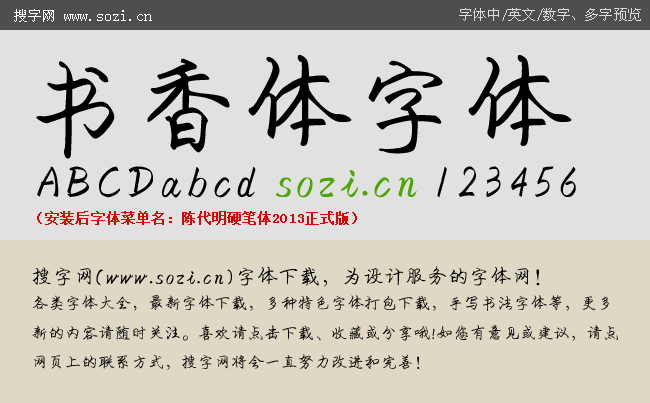
書香體字體
搜字網(wǎng)給大家提供一款手寫風格的書香體字體手機中文字體下載。這款手機字體的原形是陳代明硬筆體,是一款手寫風格書法字體,字體書寫流暢,瀟灑大方,特別適合喜歡書法的朋友在手機上安裝使用。搜字網(wǎng)的書香體等系列陳代明系列字體擁有正規(guī)版權,對本字體用于商業(yè)用途的朋友,請向作者聯(lián)系,否則追究法律責任。 QQ:641457046。電話:13194796177。微信號:chdm63。